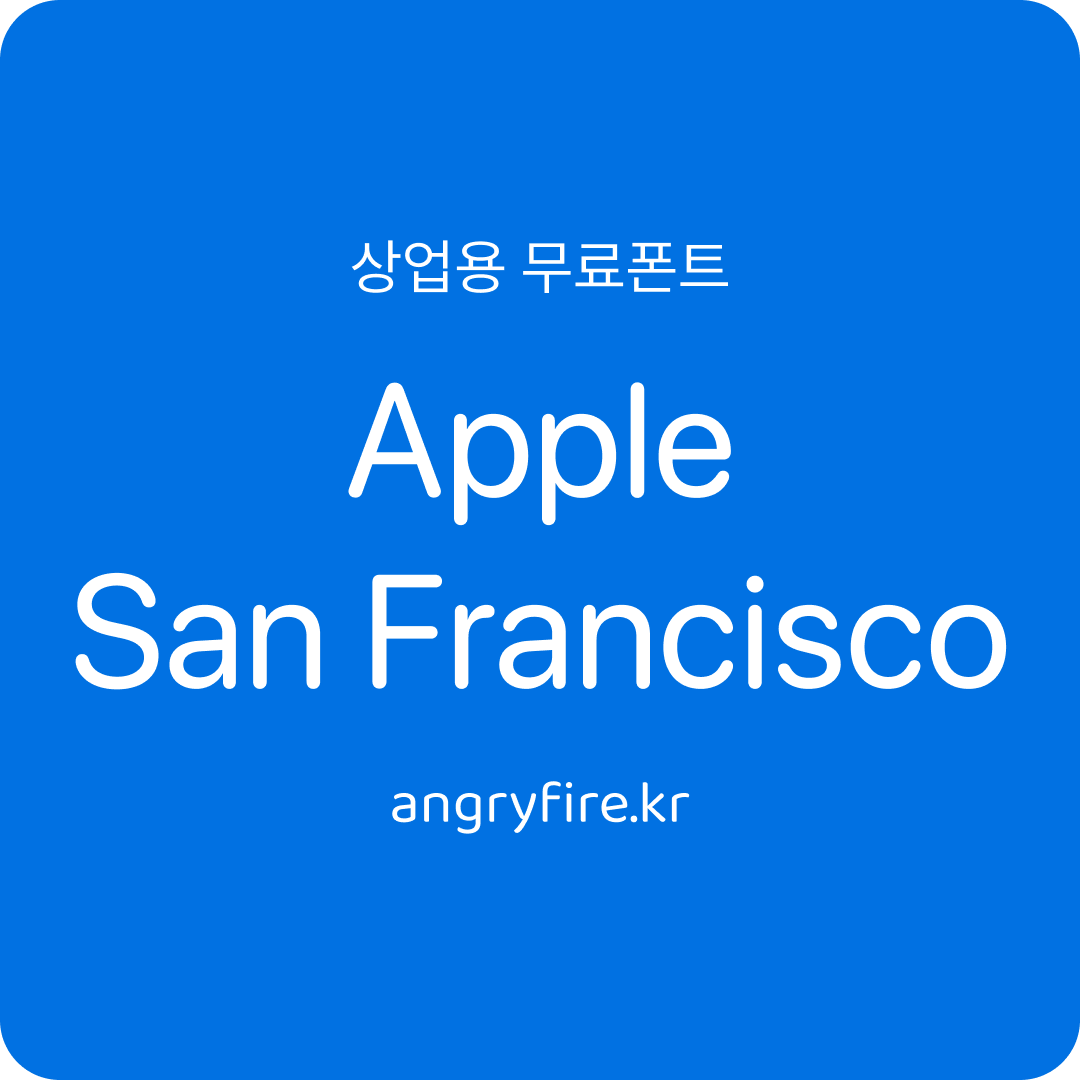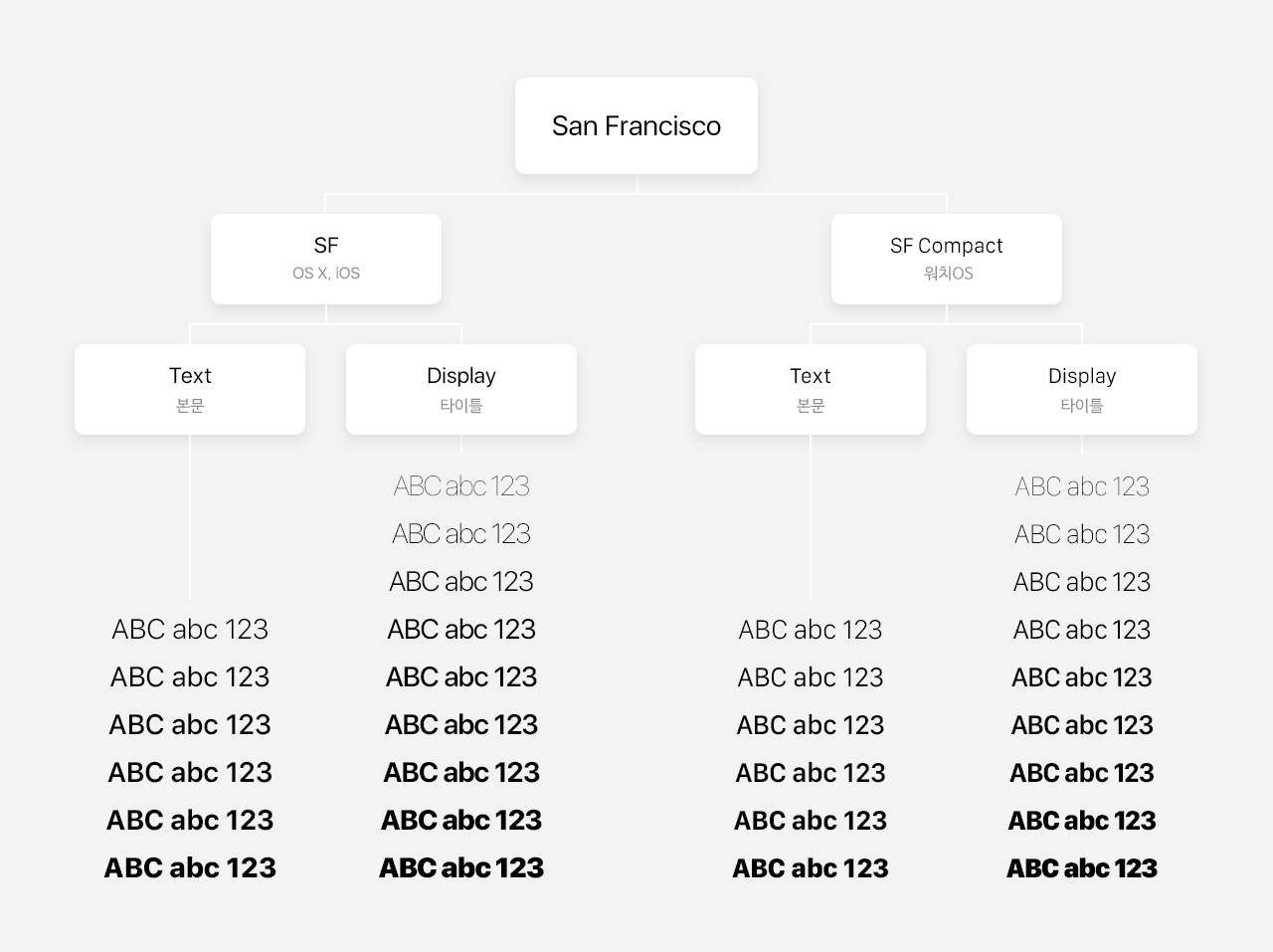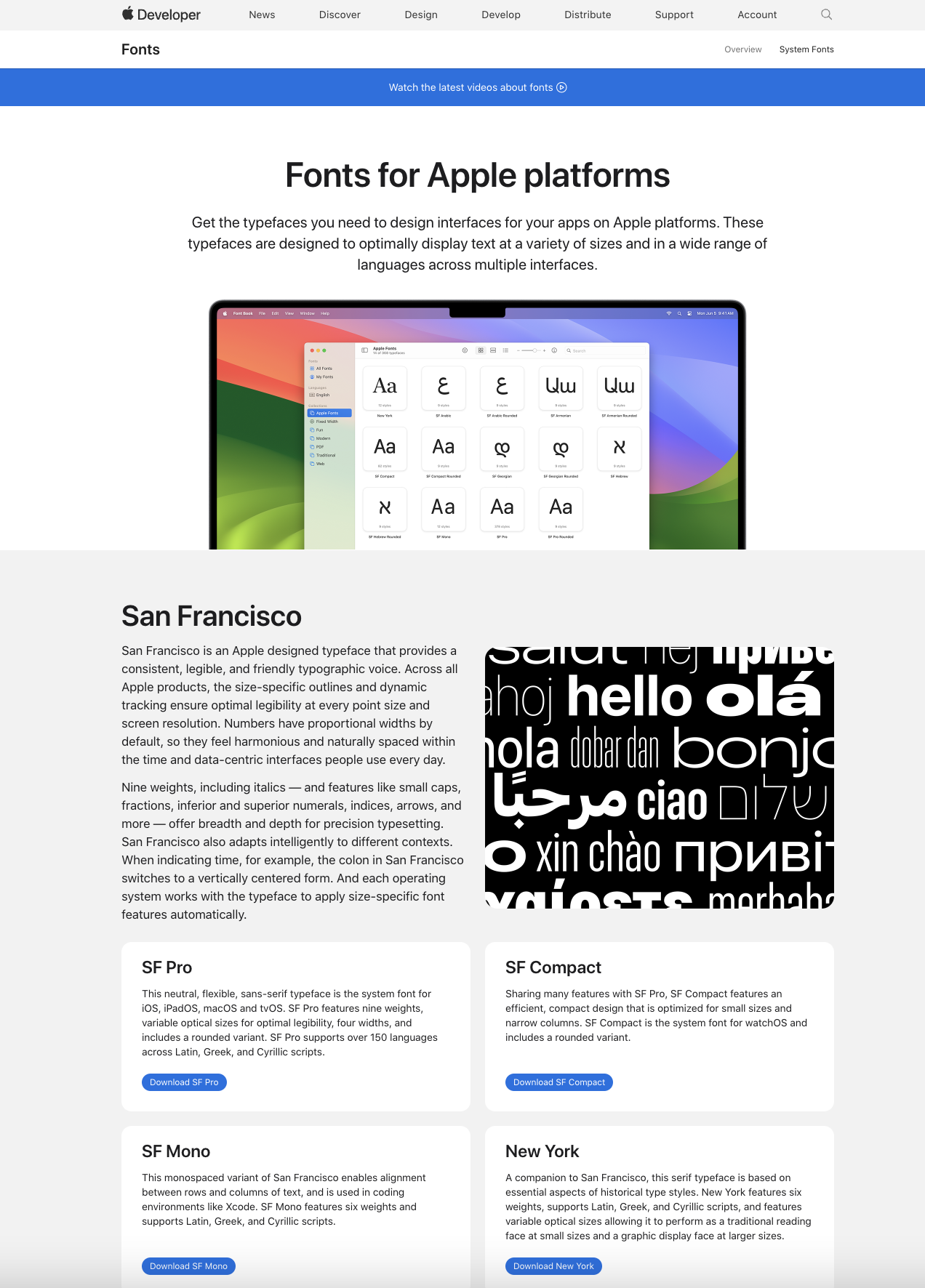
애플의 SF 폰트를 소개합니다.
iOS 뿐만 아니라 Window에서도 사용 가능한 애플의 SF 폰트입니다.
San Francisco는 일관되고 읽기 쉬우며 친근한 활자체 음성을 제공하는 Apple이 디자인한 서체입니다. 모든 Apple 제품에 걸쳐 크기별 윤곽선과 동적 추적 기능이 모든 포인트 크기와 화면 해상도에서 최적의 가독성을 보장합니다. 숫자는 기본적으로 비례적인 너비를 가지므로 사람들이 매일 사용하는 시간과 데이터 중심 인터페이스 내에서 조화롭고 자연스럽게 간격을 두는 느낌을 줍니다.
이탤릭체를 포함한 9가지 두께와 작은 대문자, 분수, 열등하고 높은 숫자, 색인, 화살표 등과 같은 기능은 정밀한 조판을 위한 폭과 깊이를 제공합니다. 샌프란시스코는 또한 다양한 상황에 지능적으로 적응합니다. 예를 들어 시간을 표시할 때 샌프란시스코의 콜론은 수직 중앙 형태로 전환됩니다. 그리고 각 운영 체제는 서체와 함께 작동하여 크기별 글꼴 기능을 자동으로 적용합니다.